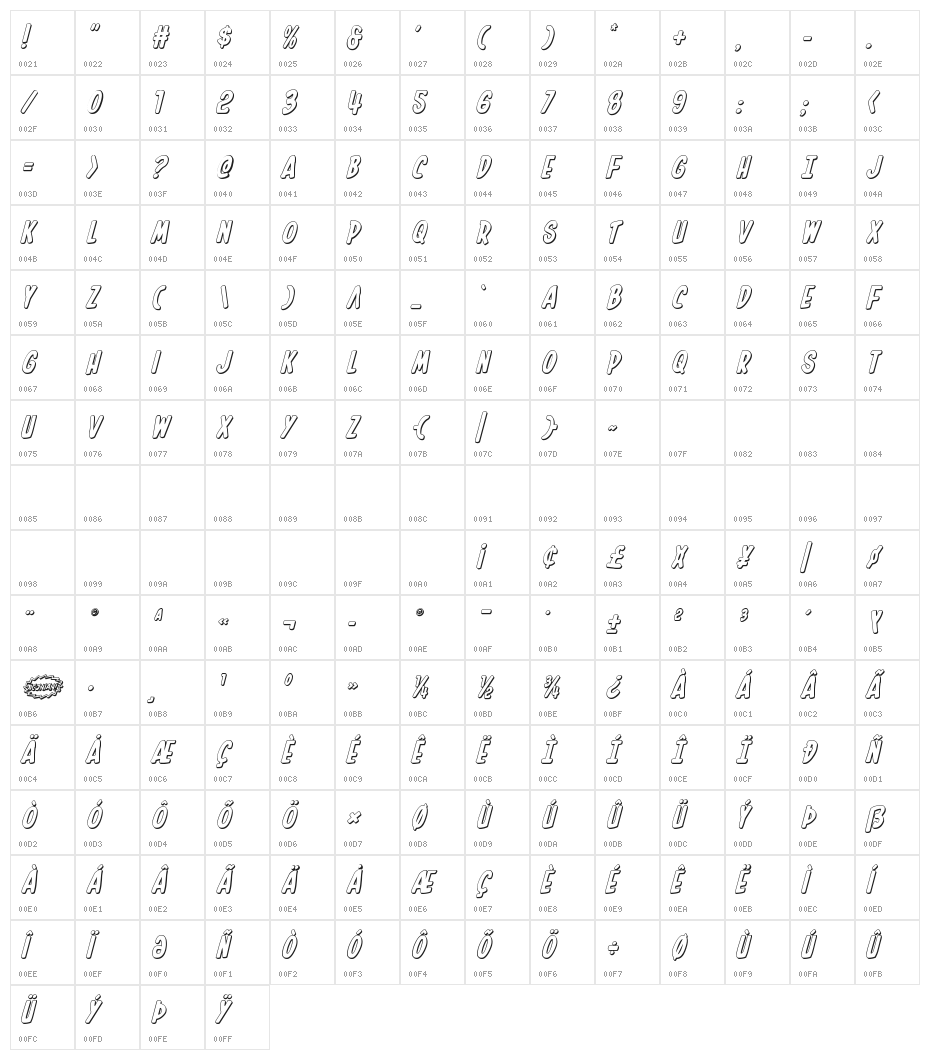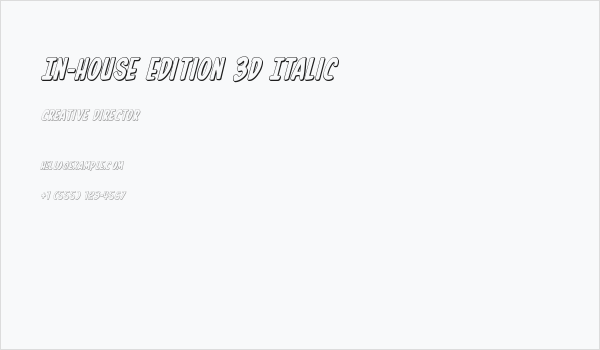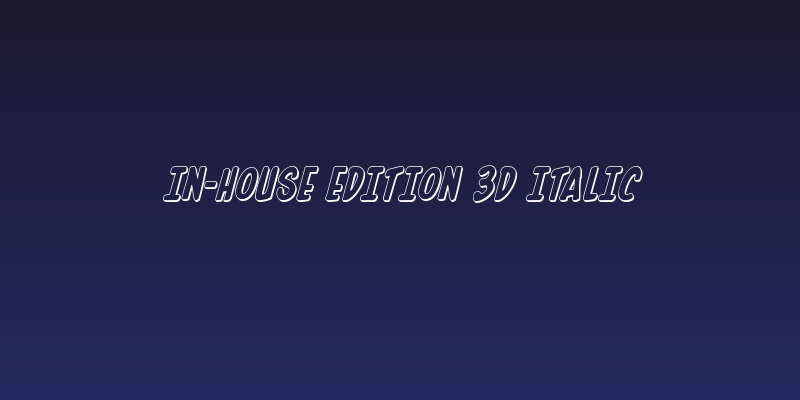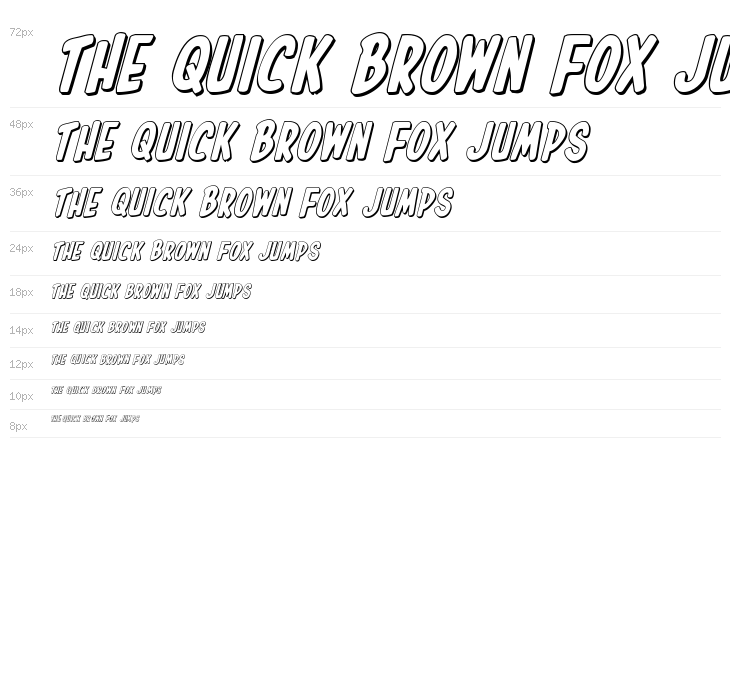
In-House Edition 3D Italic Font
| Nome | In-House Edition 3D Italic |
| Categorie | Comic |
| Stile generale | Playful, Dynamic |
| Caso d'uso | Headlines, Posters, Children's Books |
| Progetti proposti | Ideal for posters, headlines, children's books, and any design needing a fun, bold statement. |